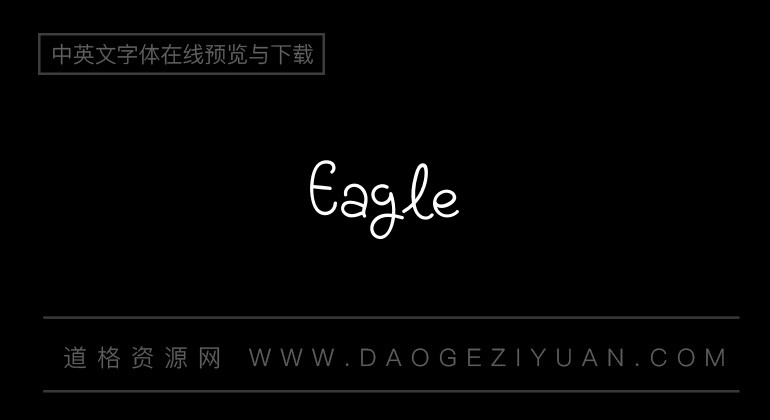
Eagle字体是一款简洁、优雅的英文字体,由英国设计师Ralph du Carrois设计,于2008年发布。Eagle字体的设计灵感来自于20世纪30年代的传统英文字体,其字形结构比较简洁,笔画较细,曲线优美,它的特点是把现代的设计元素和传统的结构融合在一起,形成了一种独特的英文字体。Eagle字体可以用于印刷、网页和视觉设计等多种应用场合,适合用于简报、书籍、标识、海报、杂志等多种设计作品。内容介绍
Eagle是一款非常不错的手写艺术字体,具有很好的视觉感,适合于文化类的宣传设计、商业类品牌的广告和产品包装设计以及个性化文字排版等较多场景。